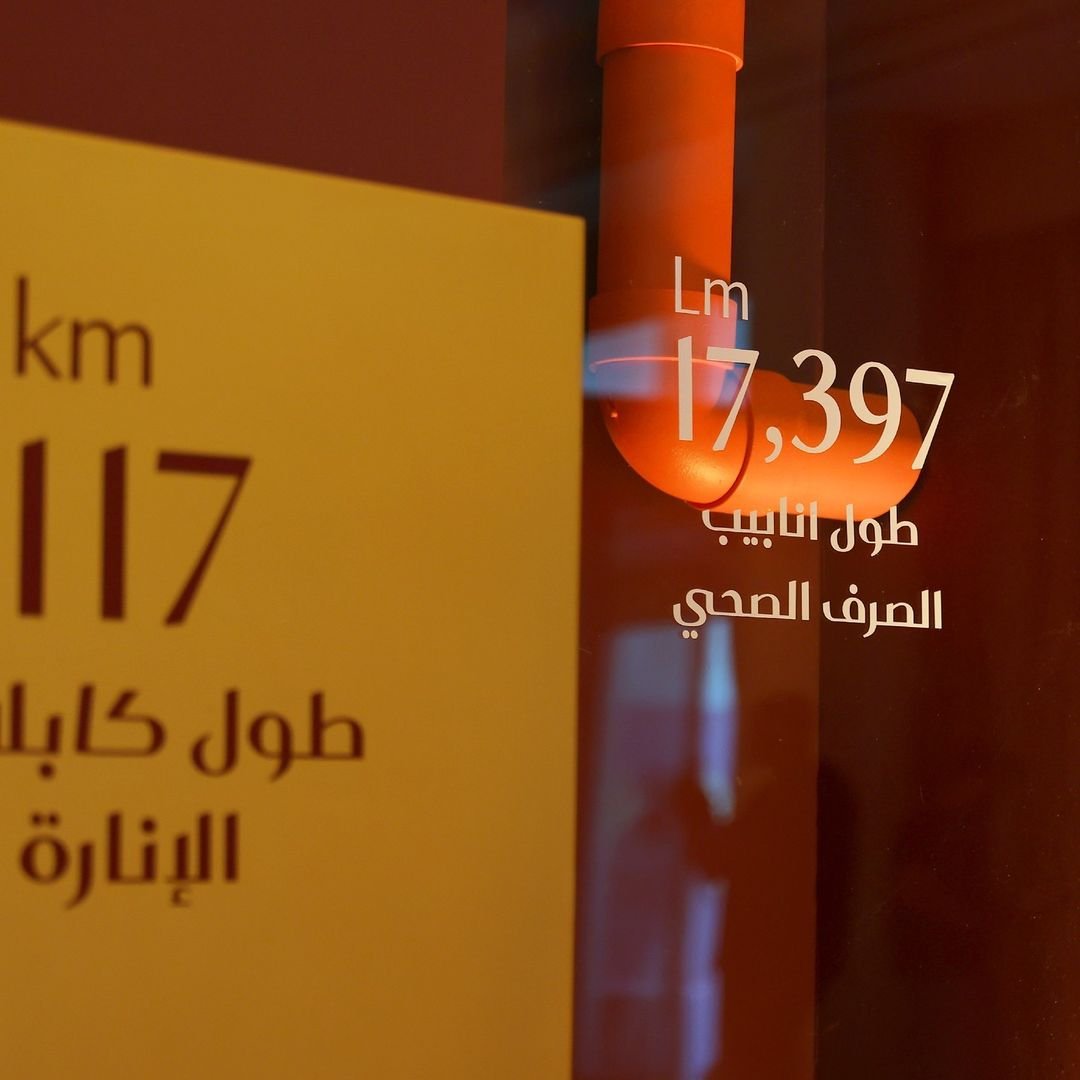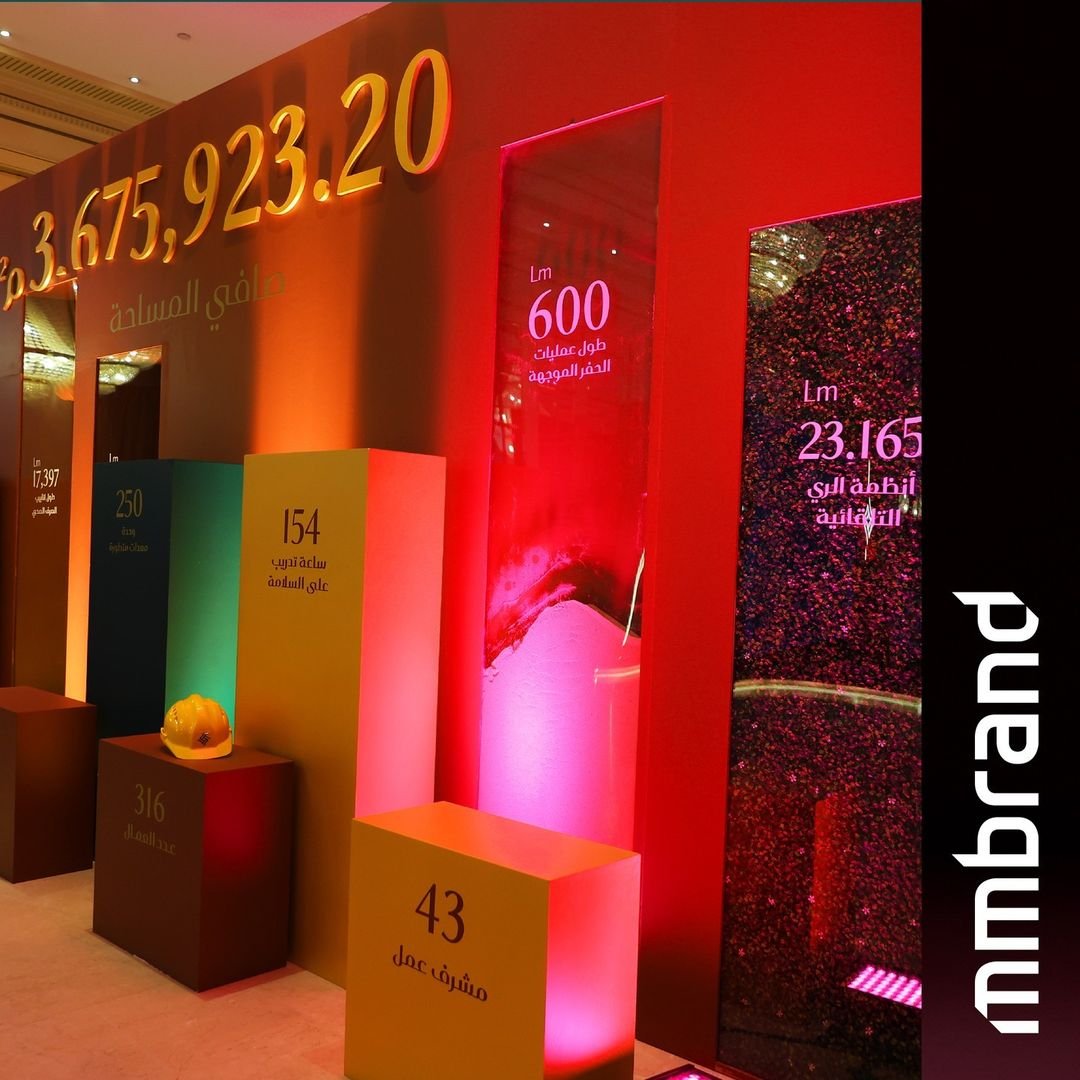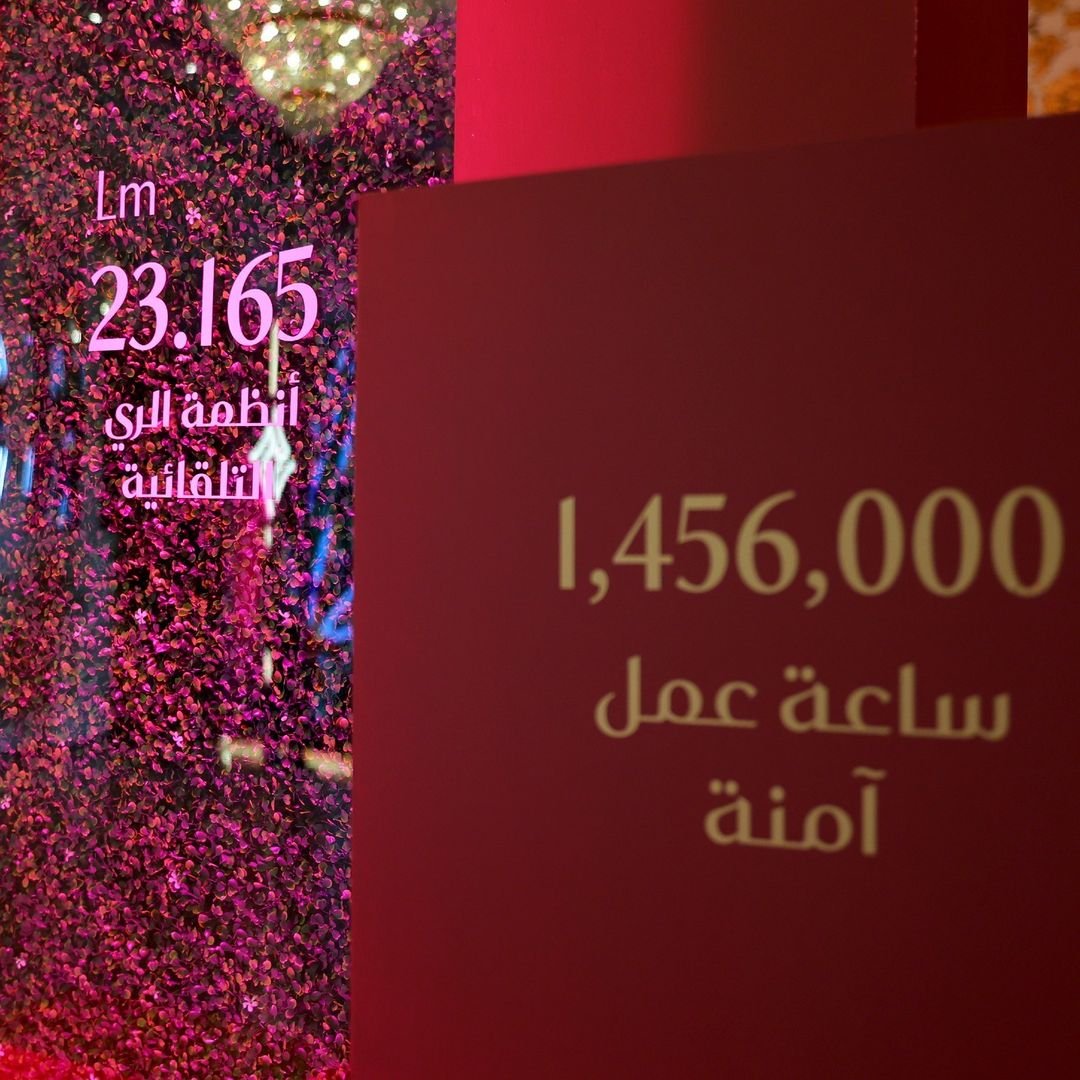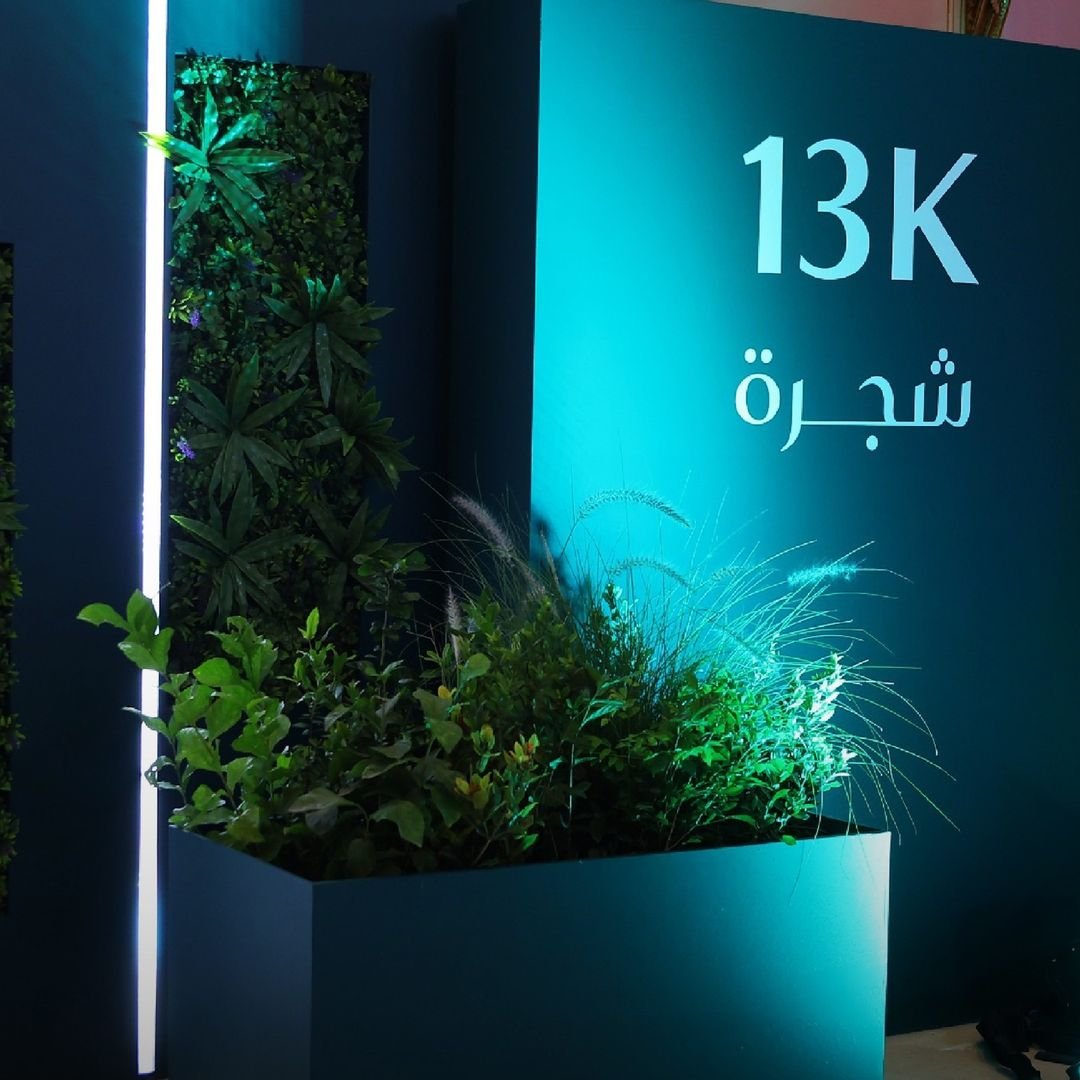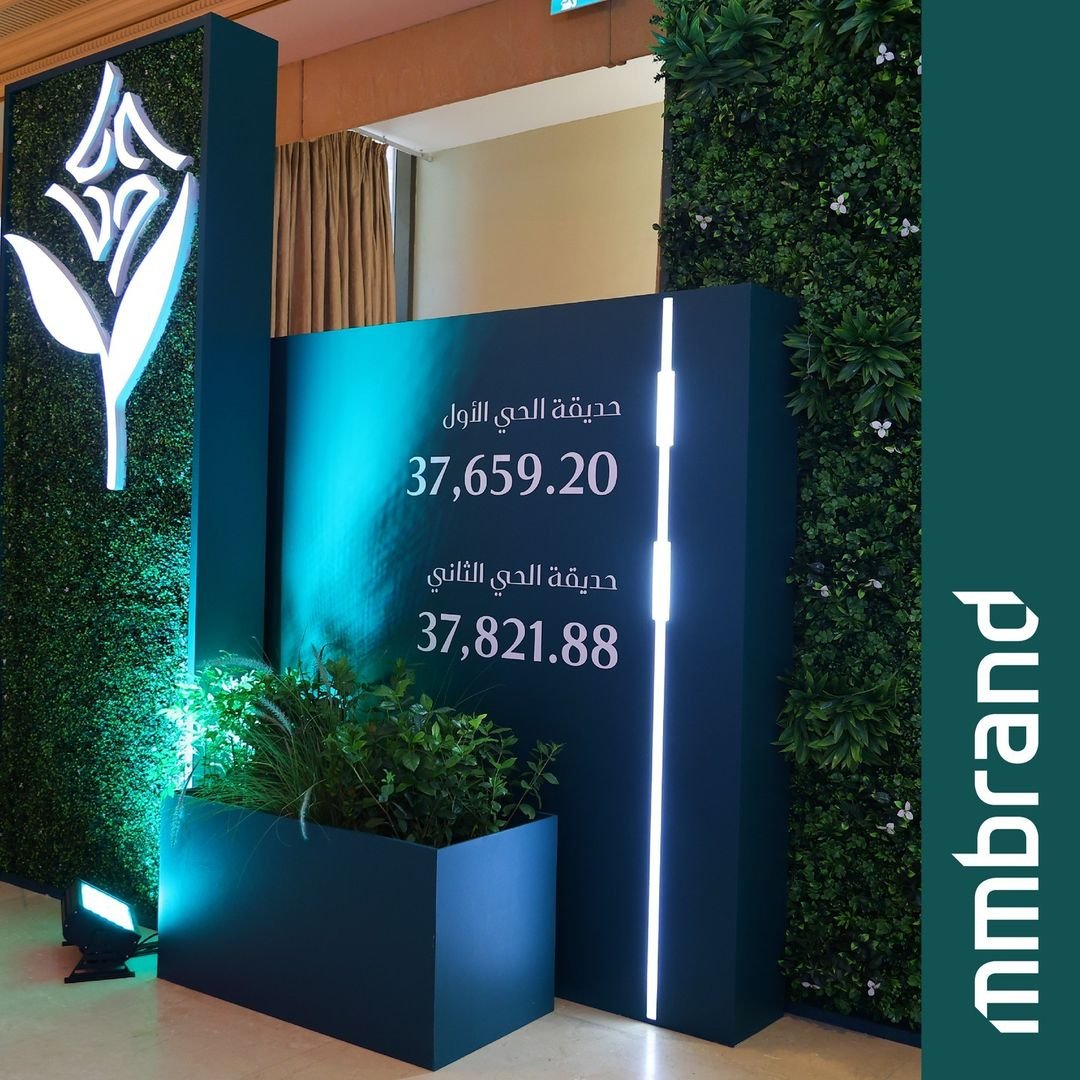
استخدام خط لورين برو – MmBrand
لورين برو هو خط عربي طباعي ذو مظهر خاص جدا. يجمع بين خصائص الأنواع المختلفة. بينما يتأثر تصميمه أسلوب الكوفي والنسخ .اختيار مثالي للعناوين الرئيسية والطباعة كبيرة الحجم وشعارات الموضة والعلامات التجارية والهوية وتصميم موقع الويب وفن الألبوم والأغلفة والملصقات والإعلانات وما إلى ذلك.